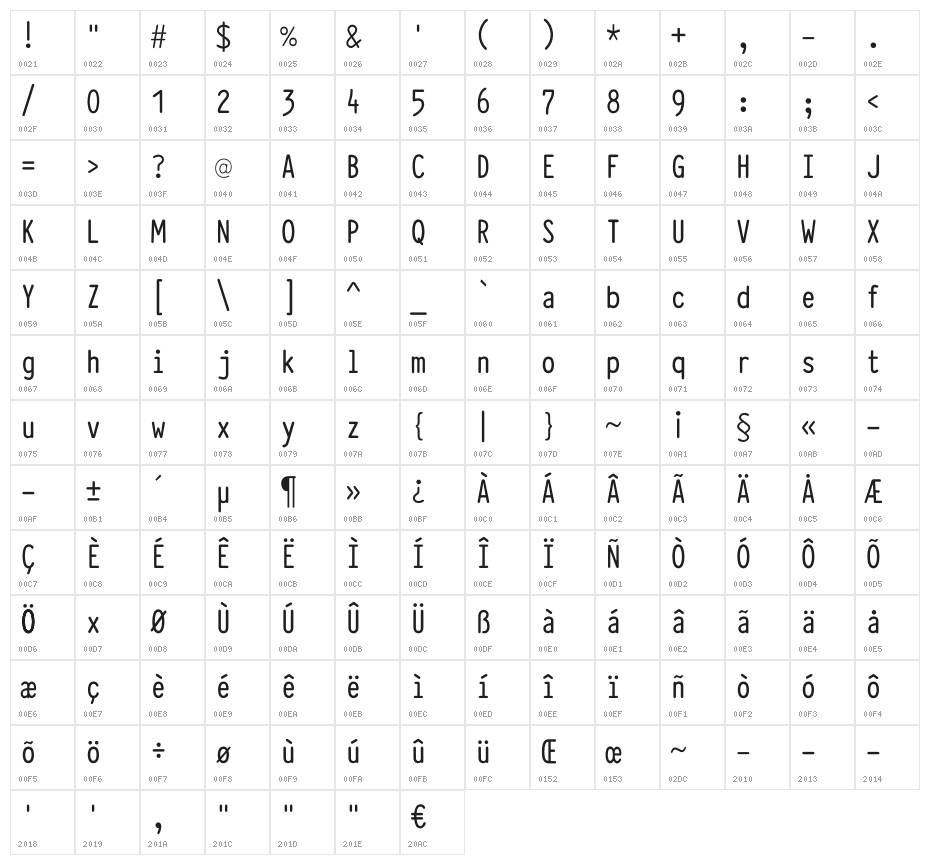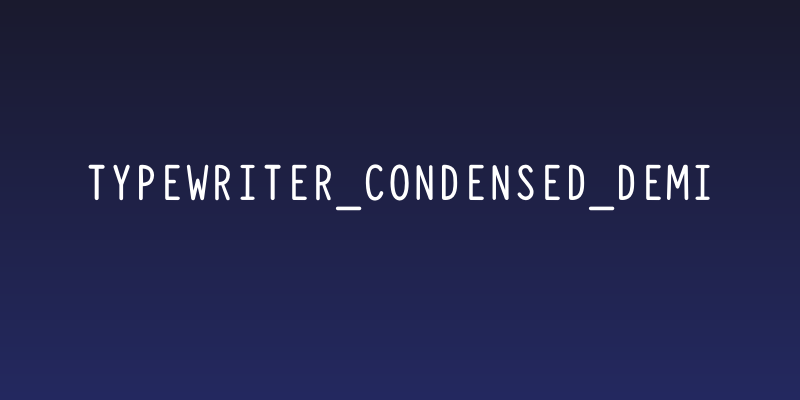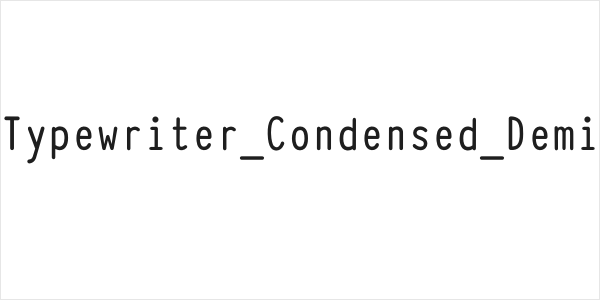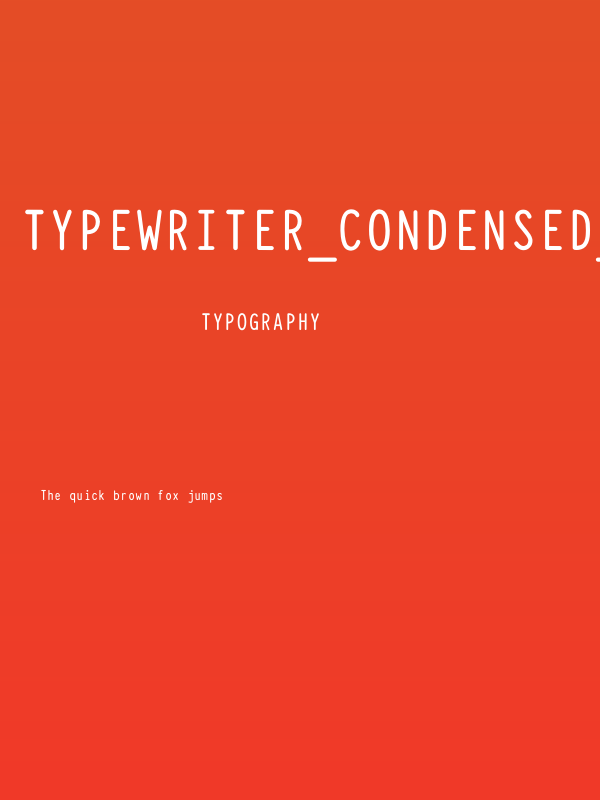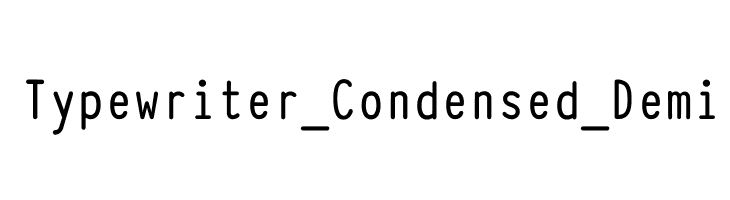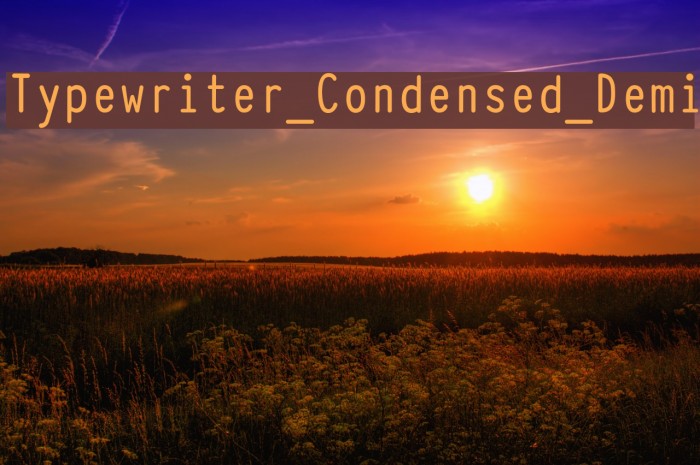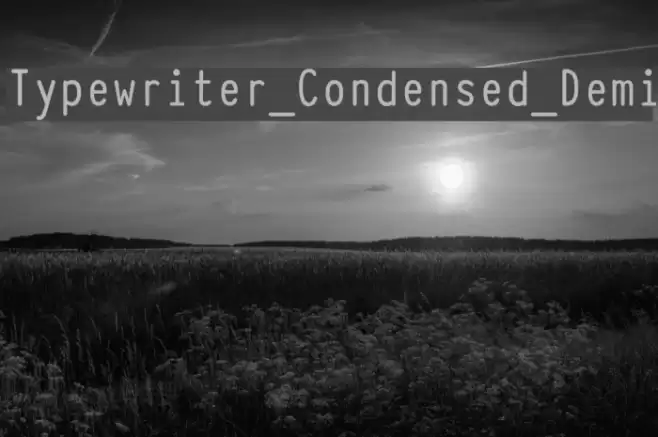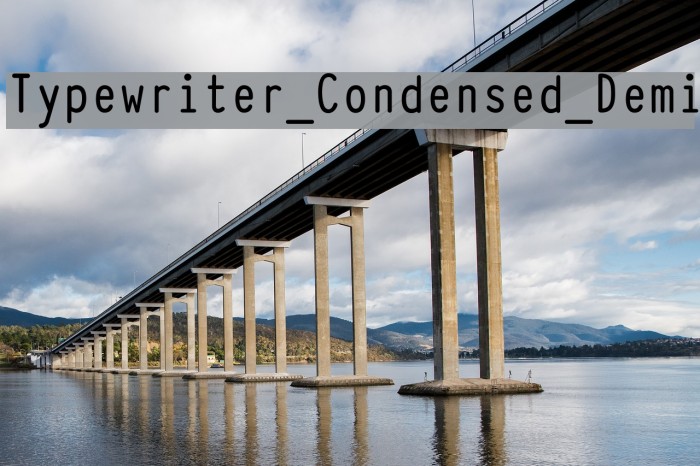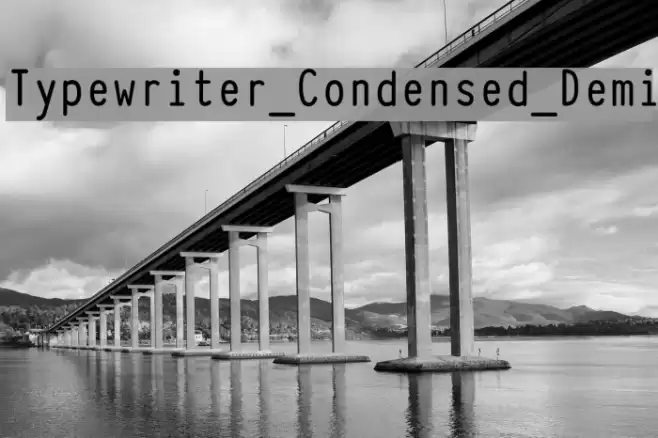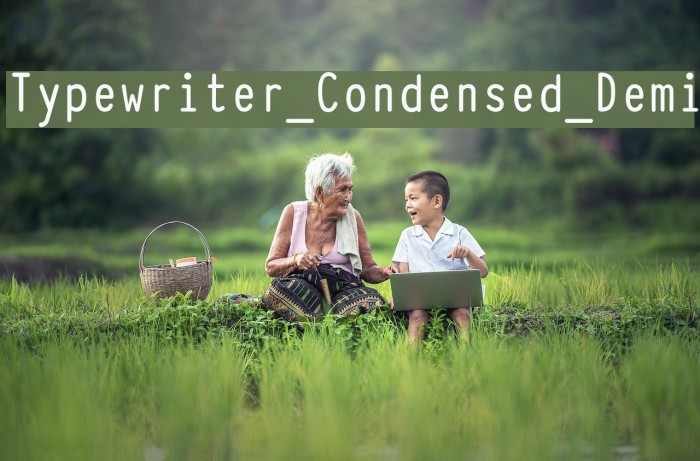
Typewriter_Condensed_Demi Font
Esta fuente incluye 224 caracteres. Haz clic en cualquier carácter para ver los detalles.
| Categorías | Typewriter |
| Espaciado de caracteres | Normal |
| Estilo general | Vintage |
| Caso de uso | Technical documents, Coding, Retro designs |
| Proyectos propuestos | Ideal for coding environments, retro-themed designs, technical documents, and any project requiring a vintage typewriter aesthetic. |
| Es fijo Pitch | Yes |